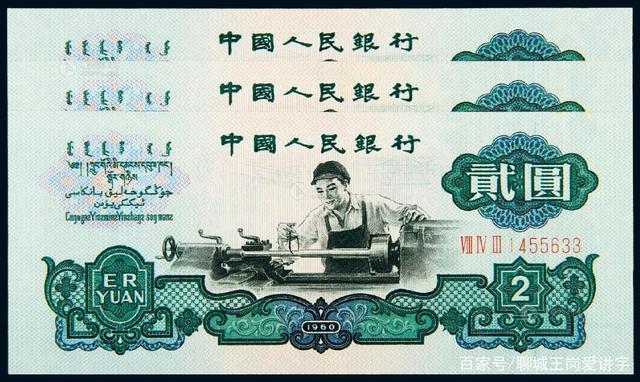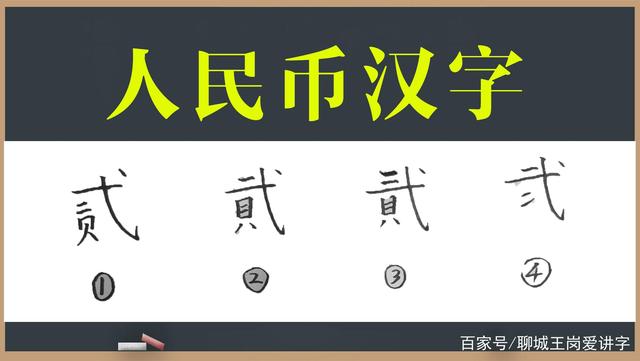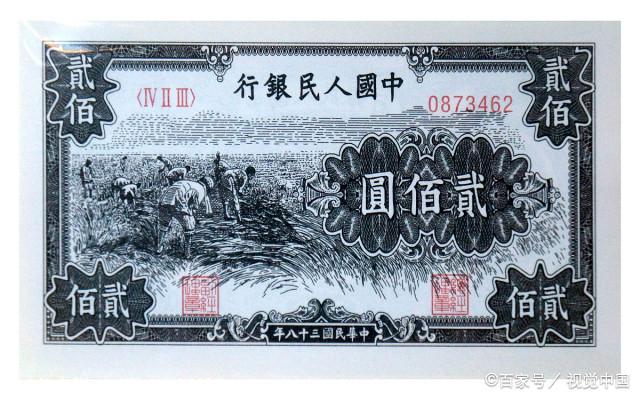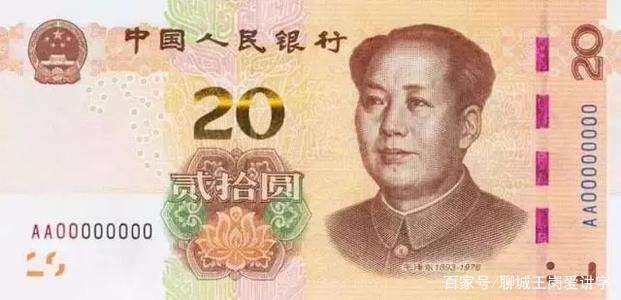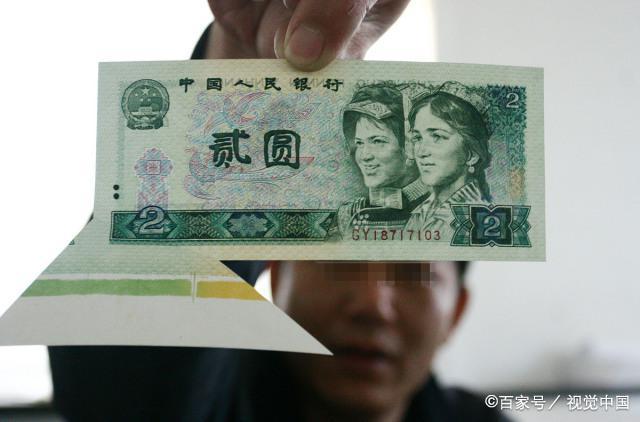
二繁体字是什么样的
二繁体字
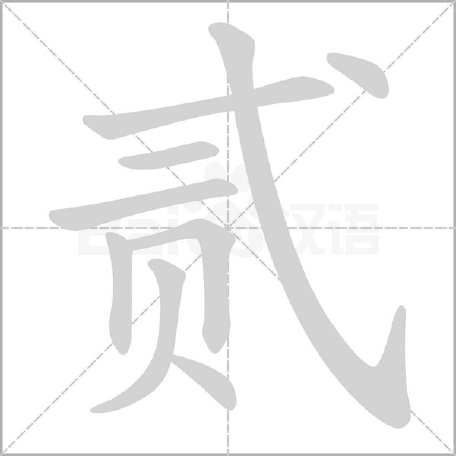
贰,汉语一级字,读作贰(èr),本意是指副;也是“二”的大写形式,用来计数和记账; 还指变节,背叛。该文字在《周礼·乃酒正》和《礼记·曲礼》等文献均有记载。
貮
貮是人民币数字,据中国人民银行吉林市中心支行办公室主任郑宝玉介绍,纸币上“二”字写在“弋”上边这种,通常会发生在中国人民银行发行的第一、二、三套人民币上,而在之后发行的人民币中“二”字一般写在“弋”的下边。
不知道大家有没有发现,咱们的人民币上数字二的大写(“贰”和“貮”)是不一样的。从第一套人民币发行到现在流通最广泛的第五套人民币上的大写的二,主要有2种不一样的书写方式!为啥钱币上的汉字没有统一?这到底有什么说法?我们简单地说道说道。
钱币上的“二”大体分两种:贰和貮(两横在上,无法打出来)
关于大写汉字“二”,钱币主要有2种写法分别是:贰和 貮(两横在上) 。有人认为正确的应该是贰,其他的都写错了,或者说是印错版了。这种说法纯属无稽之谈,钱币这么严谨的问题怎么会出现错别字?之所以会出现这种情况是跟当时的文化情况有关。可以肯定的是:它们不是错别字,是数字“二”的大写形式。
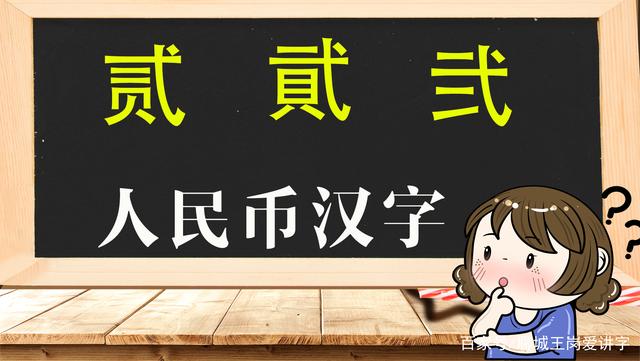
数字汉字“二”有哪些表现形式:
总体算下来数字汉字“二”有4种表现形式(请看下图)。仔细看这4个字10秒种,你会发现它们的不同,我们逐个分析下:
第一个“贰”:它的结构是里面的“二”和“贝”写在了‘弋yì’的下边,整体看上去更舒服一些,这个“贰”字也是目前最认可,用的最多的“贰”字。现在新版的为汉字“贰”。
第二个“貮”:“貮”与“贰”的区别为:贝变成了繁体的“貝”,然后‘弋’的上面增加了一横。
第三个“貮”(两横在上):无法打出来,只能表述了。它的特点为:‘弋’的上面增加了两横,这个“貮”(两横在上)也是在第一套、第二套、第三套人民币上用得最多的汉字“貮”(两横在上)。有人说这两横写在上面的汉字是个错别字,因为《康熙字典》中没有。我反对这种说法,字典中没有的字不代表它就不存在。
第四个“弐”:现在用的几乎很少了。但在以前的那个年代,“弐”字更多比较很广泛,更多地出现在民间的借贷上。比如:手写契约,或者是立字据、写收条等方式。
汉字“二”的四种表现形式汉字“贰”和“貮”(两横在上),在一开始就没统一
有些人可能还记得,在第一套人民币发行时,带“二”的钱币上没有2元的,只有20元和200元的。也就是说从一开始也就没统一整合起来,当时的钱币上的“二”是:“贰”和“貮”(两横在上)。关于为啥一开始就这样,有多个版本的说法,这里也不妄下结论。我个人的分析是:1948年发行第一套人民币,当时我们新中国还没有完全统一,各项机制等都不是十分健全。发行的货币图案多以表现我国建设自力更生、艰苦奋斗的情景画面,而关于上面的更多以繁体字出现。当时的汉字简化改革不像现在这么彻底。
貮”(两横在上)第二套人民币发行时,更多的推广汉字“貮”(两横在上)
到了1954年第二套人民币发行时,我们国家对钱币的管理更加规范化,对钱币整体的字体大小、字体格式进一步的进行了完善。因为当时的社会背景,我国正在健康稳定地恢复国内生产,一切都在井井有条的进行中。钱币作为我们国家的经济象征,要更加规范。为此当时还邀请了著名的金融学家和书法家马文蔚先生来亲自参与设计。马先生从防伪、美观等多个因素来考虑,最终选择了半隶、半魏碑的字体,因为这样的字体相对来说更加的扁平,也就是在这种字体的模式下,“贰”通常写成“貮”(两横在上)。这个“貮”(两横在上)被广泛用在了第二套人民币的二元、二角和二分纸币、硬币中“二”。
二分钱第三套人民币的“二”模式,延续了第二套的方法
正是由于第二套人民币在当时流通了很久,影响很大。此后的人民币版本都是按照之前的字体来设定的。以至于咱们现在看到市面上流通的1分的2分的5分硬币还在流通。据说还有专门收购带这个字体贰的硬币。由于50年代发行的貮分硬币时间早,量不大,相对来说收藏价值还是很高的。
还是有收藏价值的第四套人民币发行统一为“贰”,分除外
直到第四套人民币的发行,纸币上必须统一上面的贰字。于是除了分之外,其余的统一变成了“贰”。这样的统一也顺应了汉字的简化改革,从而使现在的汉字“贰”占据了主动地位。而其他三种形式的汉字“二”并没有退出历史舞台,只是以其他的形式来展现它们的存在。
第四套人民币的贰元第五套人民币汉字“贰”:一览众山小
到了1999年发行的第五套人民币的“贰”字,它的地位就可以雄霸天下、一览众山小了,但没有完全统一,因为“貮”分的一直都在,没改变。其实任何事情都是这样的,汉字在使用上都有这个规律,就是统一化、规范化、大众化。现在看这个“贰”字,标准现代字体的简体方式,也可以说是众望所归吧。
贰拾元结束语:通过本文的介绍主要想跟大家分享:我们的汉字存在就有它的道理。有些汉字现在可能用得很少,或者以后基本不用。但不可否认,在历史变迁过程中它们都直接地参与了社会的发展,为人类的进步做出了很多贡献。我们尊重它们,尊重它们曾经做过的贡献,汉字没有糟粕,也没有一个是多余的,只能说我们对它们的认知还不够。